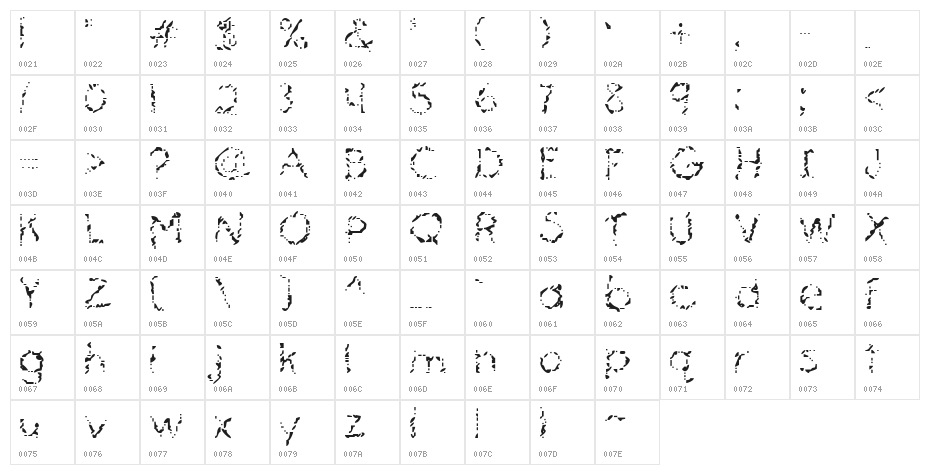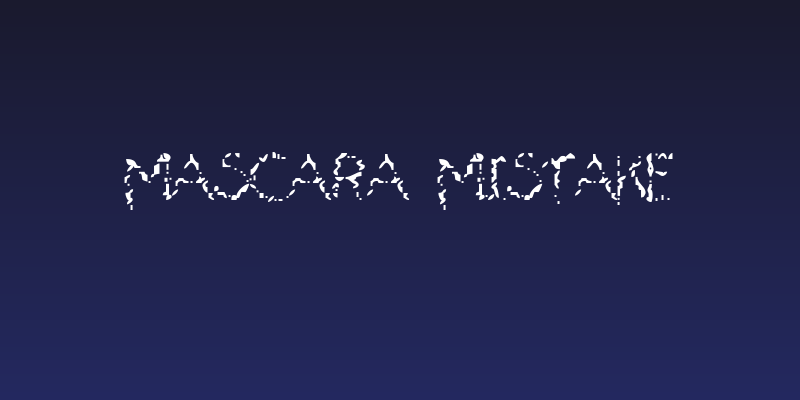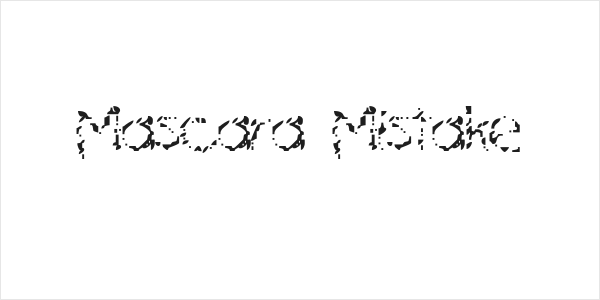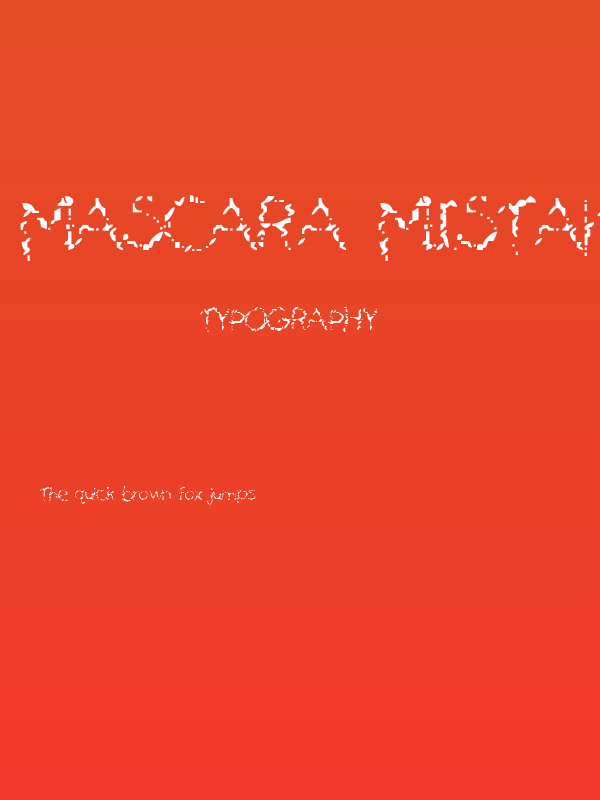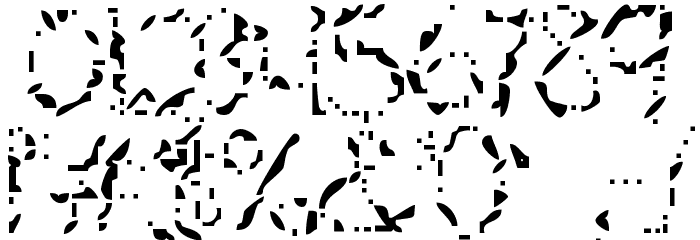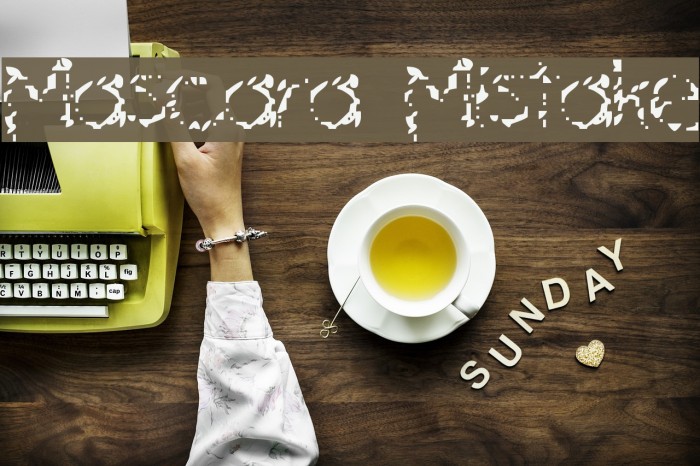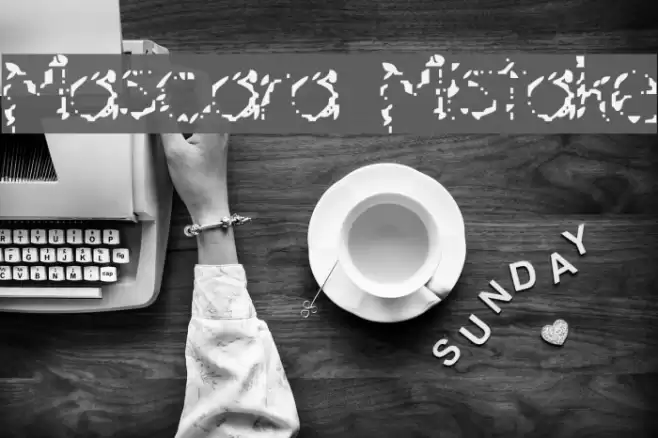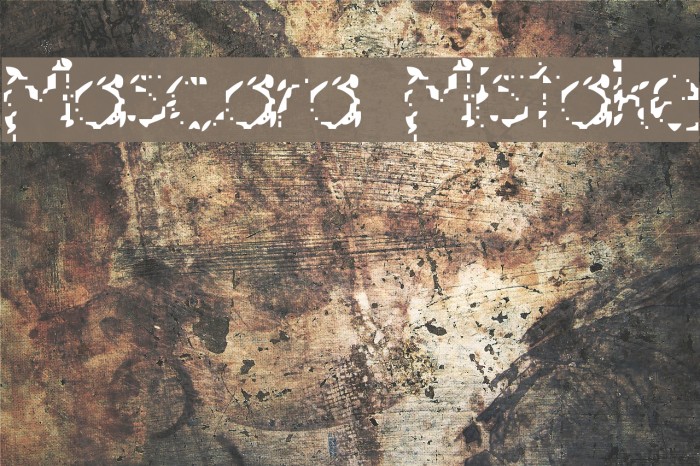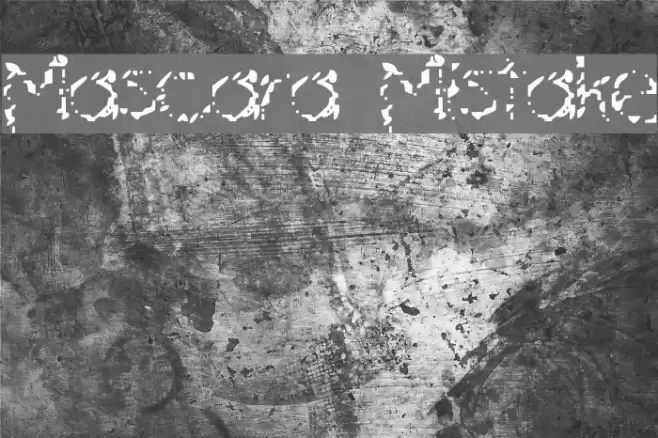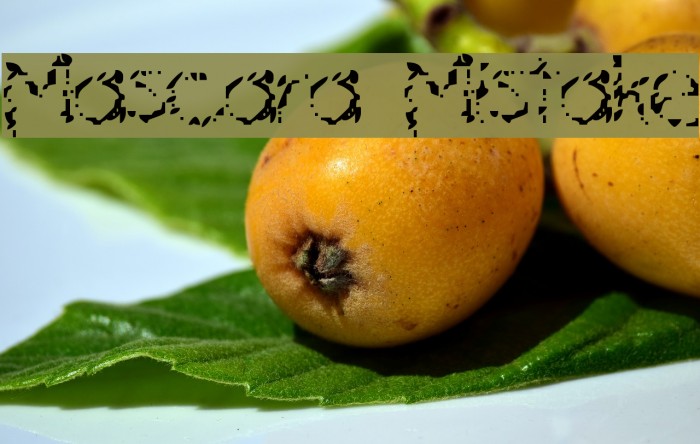
Mascara Mistake Font
✎ Broken
| الفئات | Broken |
| حالة الاستخدام | Headlines, Logos, Artistic designs |
| مشاريع مقترحة | Ideal for artistic projects, album covers, posters, and any design that requires a bold, unconventional look. |